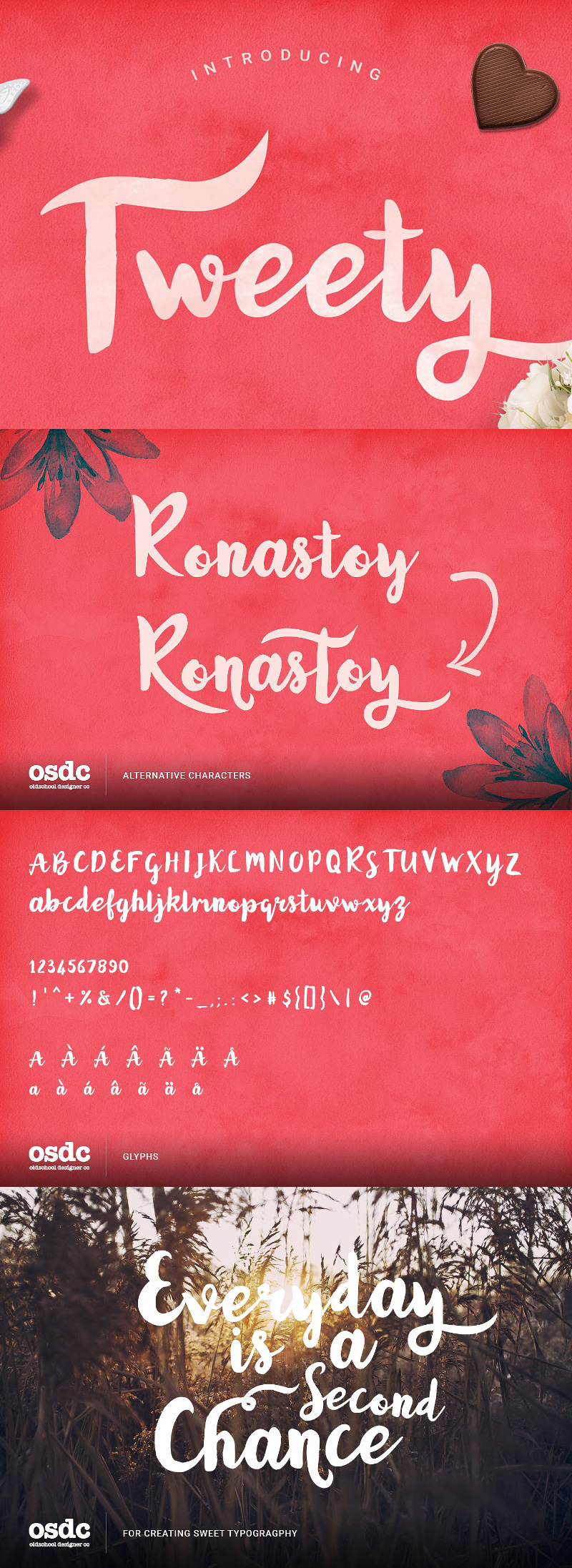
Дополнения Шрифты Татьяна Гапонова 17 мая 2017 Шрифт - Tweety Прикольный рукописный шрифт для дизайнеров. Формат - OTF. Размер - 0,8 мб. Скачать Шрифт - Tweety